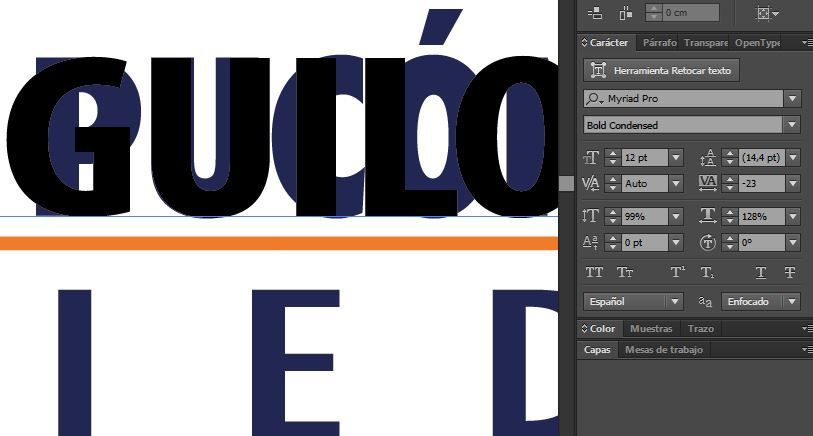
Necesito ayuda con tipografía en Illustrator CC
Estoy tratando de modificar el texto en un logo, estoy usando la misma tipografía.
El texto con azul que está debajo del negro es el que quiero igualar, el texto en negro queda más separado y más delgado (que es sólo la tipografía). Entonces necesito que me ayuden, si alguien sabe como puedo dejar el texto en negro igual que el azul se los agradecería un montón!!
Pero si lo tienes al 128% en horizontal, cómo te va a coincidir :-)
Pero es que el kerning de los caracteres es diferente.
Pensaba en hacer letra por letra, pero no tengo todas las referencias de las letras. Suponía que había una forma de hacerlo con todo el texto.
<Digo, por que no conviertes a curvas y reposicionas las letras?